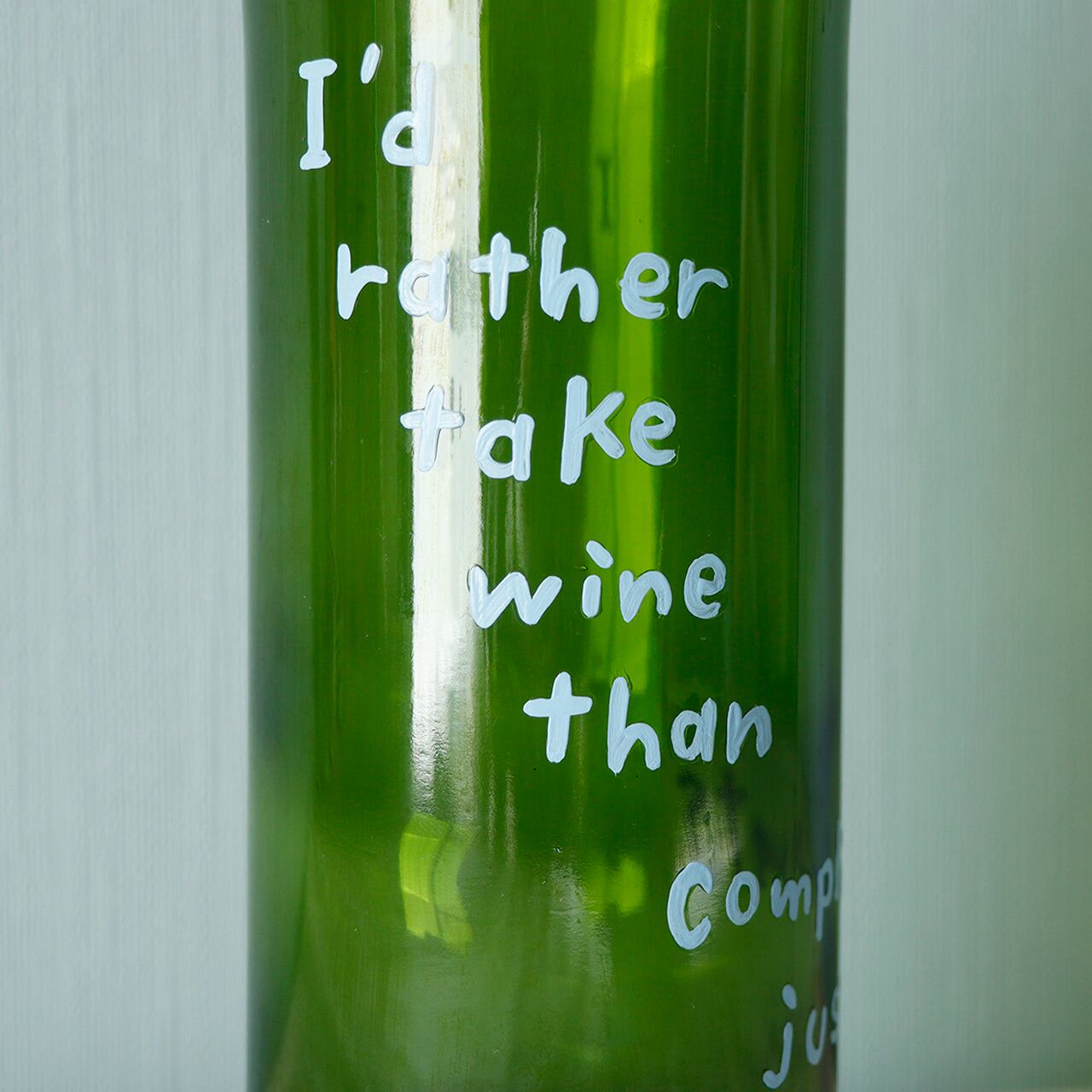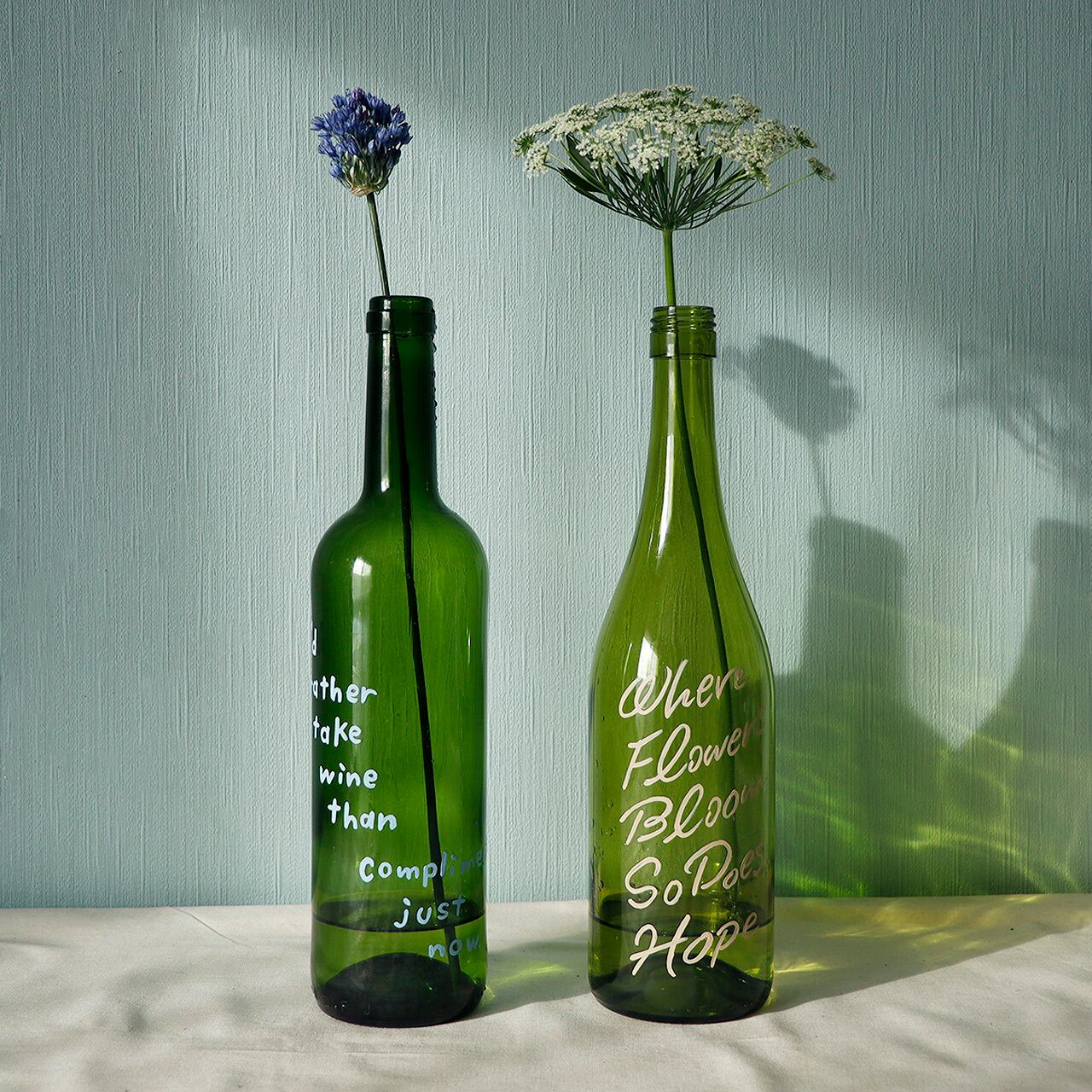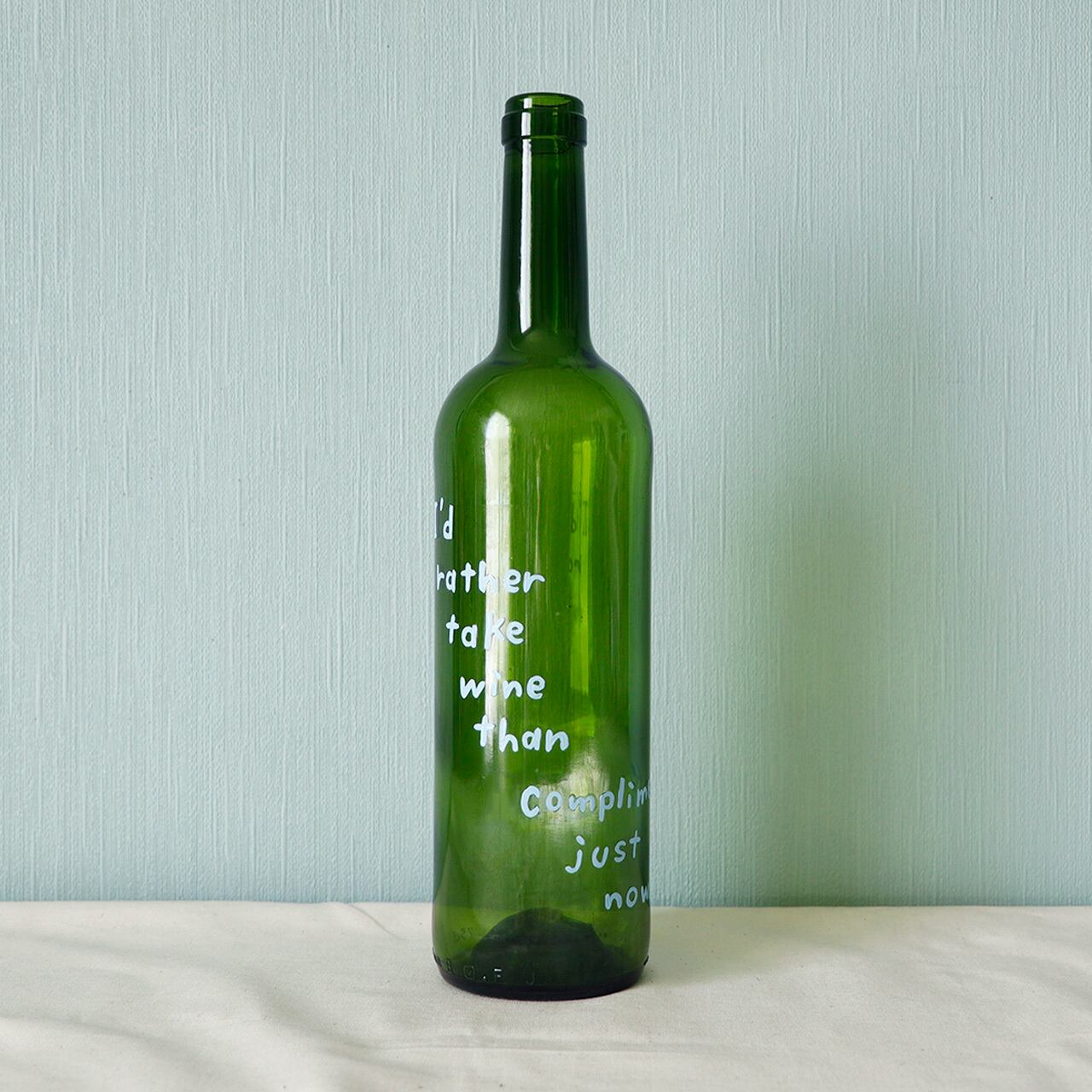
【BOTTLE PAINT ART】I’d rather take wine than compliments just now.
ワインボトルにペイントした、気軽に飾れるアートな作品が登場!
I’d rather take wine than compliments just now.
今は褒め言葉よりワインがほしい
ワイン好きな人には共感される言葉かも???
光が入るとこに置くと、瓶の色とともに文字も影になって素敵ですよ!!